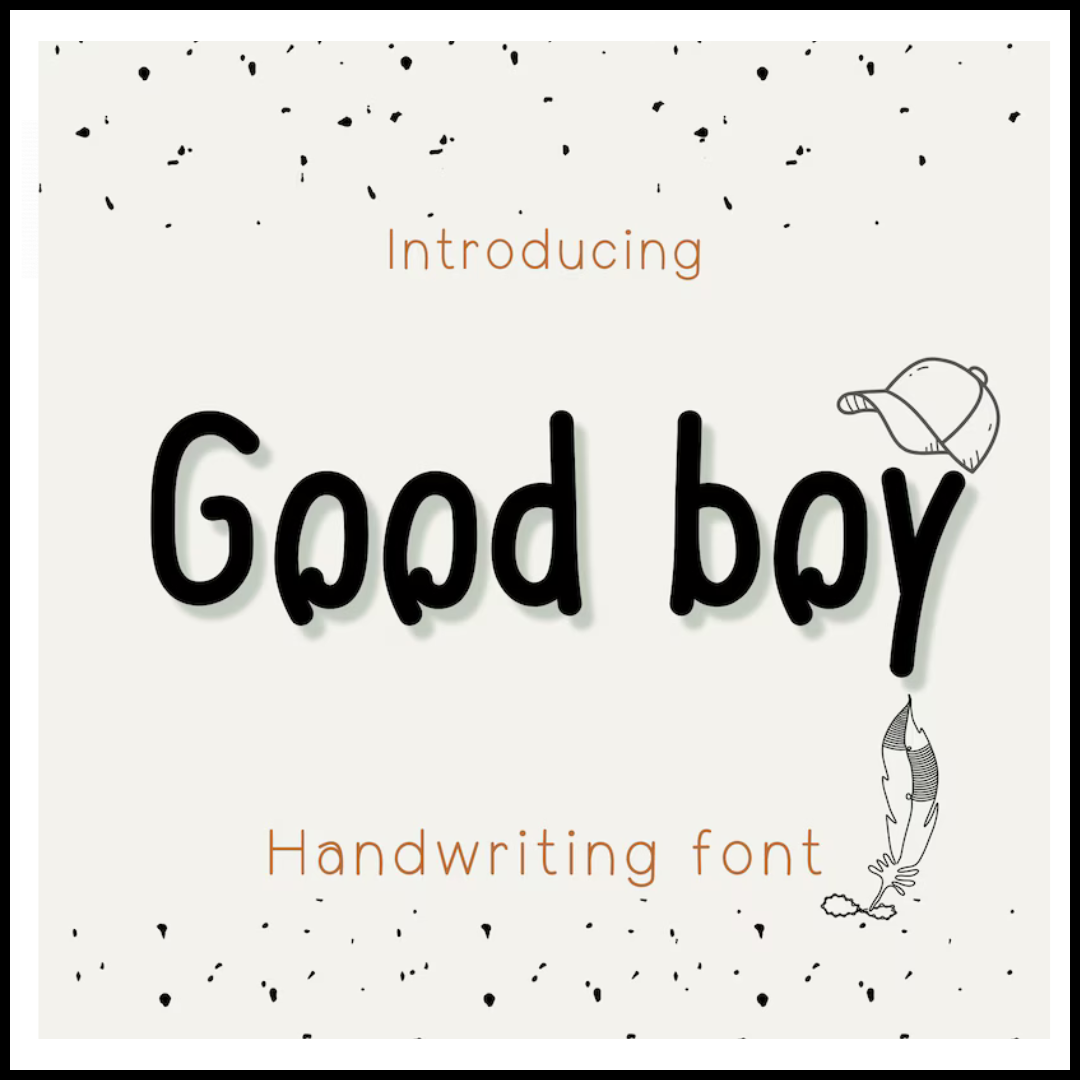
???? Good Boy Font – خط عصري بلمسة مرحة وإبداعية ????️
اجعل تصميماتك تتحدث بصوت مختلف مع Good Boy Font – الخط المثالي للمبدعين الذين يبحثون عن التميز!
هذا الخط الفريد يمزج بين الطابع اليدوي واللمسة العصرية، مما يجعله خيارًا مثاليًا للمشاريع التي تحتاج إلى طابع ودود، شبابي، ومرح.
سواء كنت تعمل على شعار، دعوة، منشور على السوشيال ميديا، أو حتى تصميم منتج رقمي، فإن Good Boy Font سيضيف لتصميمك لمسة شخصية فريدة تجذب الانتباه وتبث الحيوية في المحتوى.
???? لماذا تختار Good Boy Font؟
مظهر غير تقليدي يعكس الإبداع.
مثالي للمصممين، المدونين، وأصحاب البراندات الصغيرة.
✨ أطلق العنان لخيالك، واجعل تصاميمك أكثر دفئًا وحيوية مع خط Good Boy.